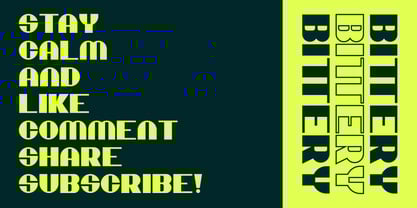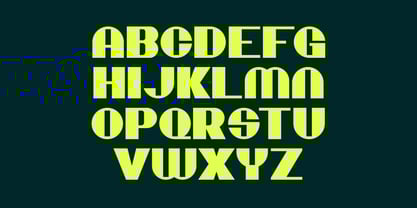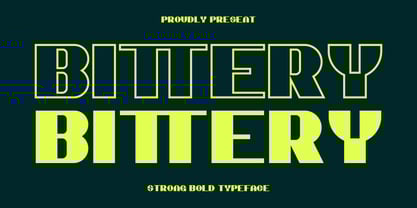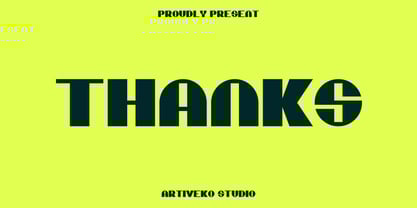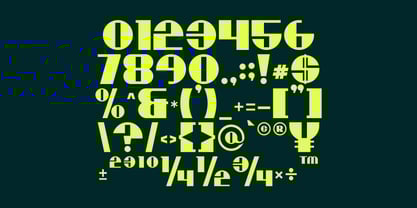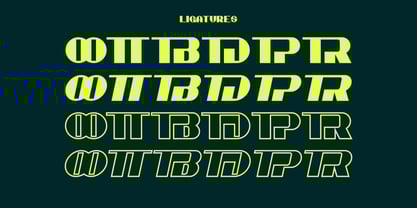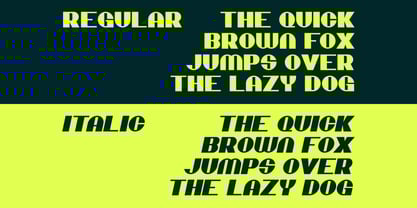
Bittery
von Artiveko
Die Schriftfamilie Bittery wurde von Iwan Alwan entworfen und von Artiveko veröffentlicht. Bittery enthält 2 Stile und Familienpaketoptionen.
Etternal is a strong bold display font built to stand out. With powerful letterforms and confident curves, it’s perfect for headlines, posters, logos, and impactful branding. Featuring multilingual support, ligatures, and alternates, Etternal delivers a bold statement in any design, combining strength with style.